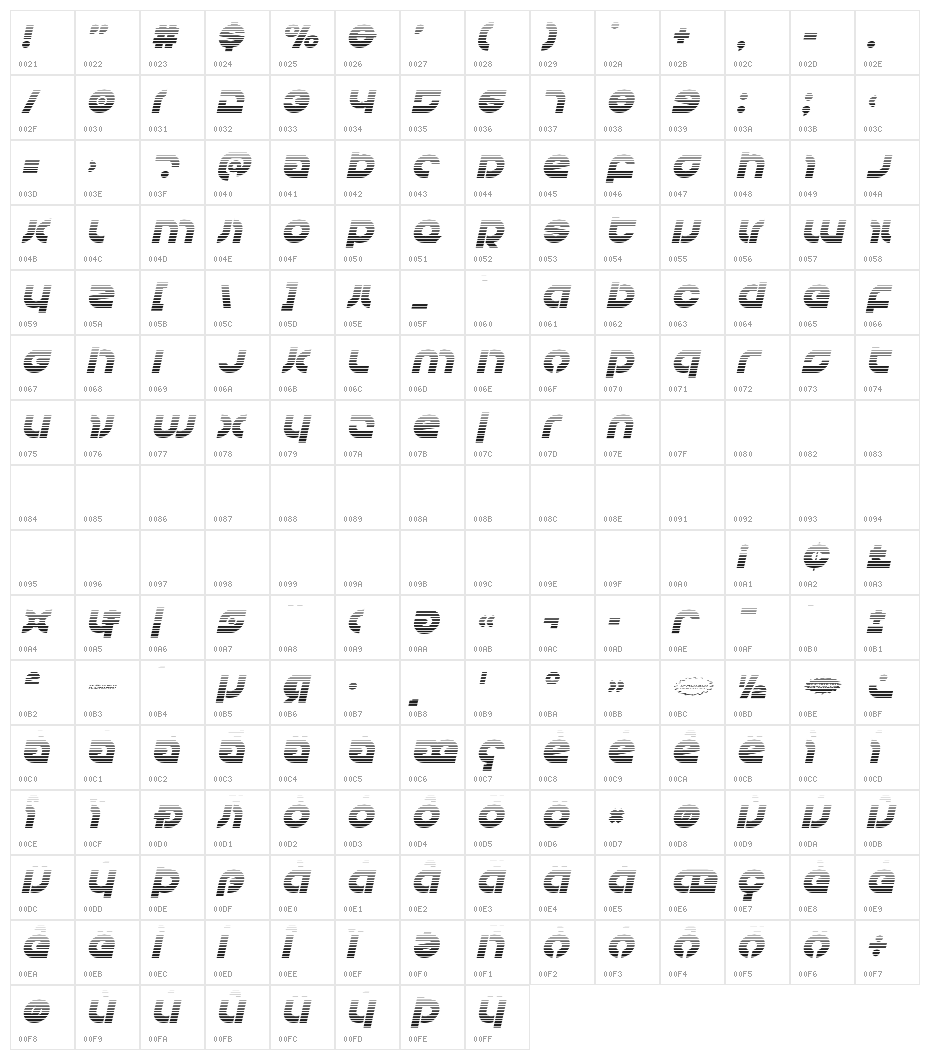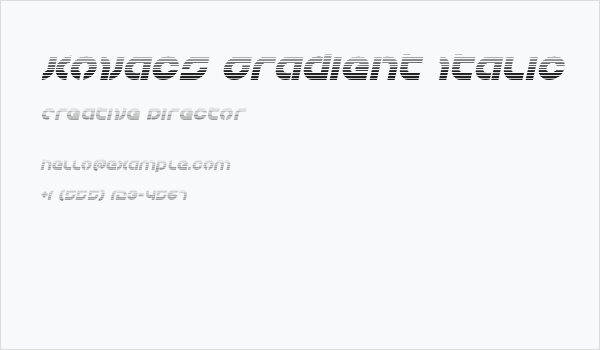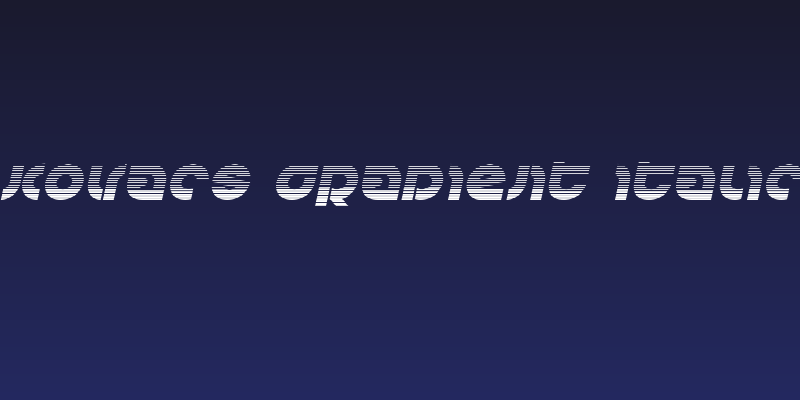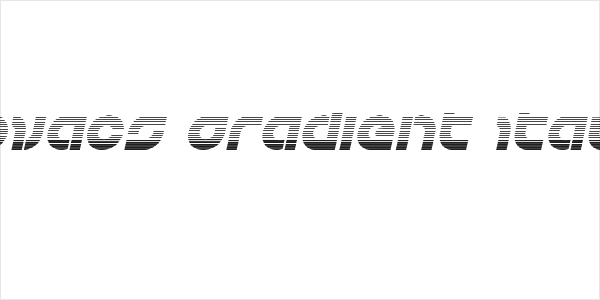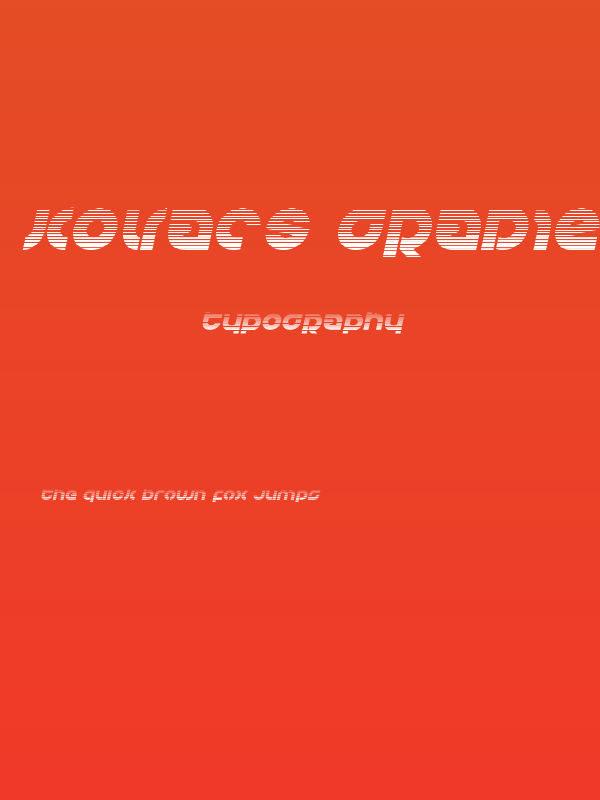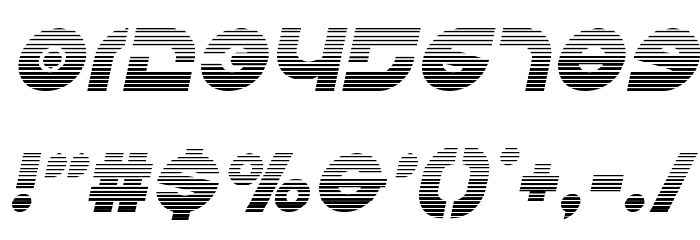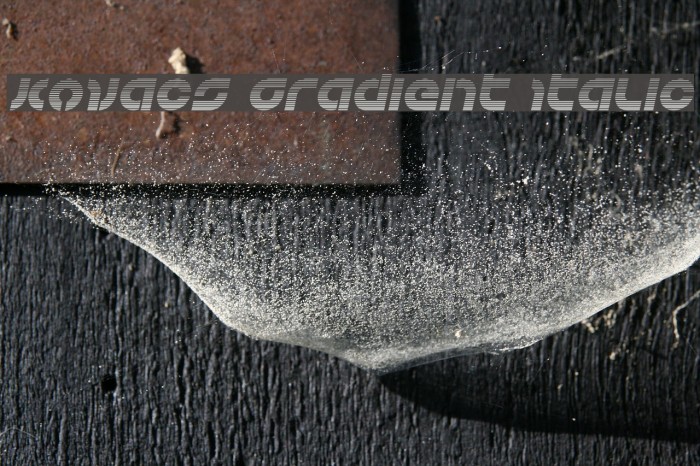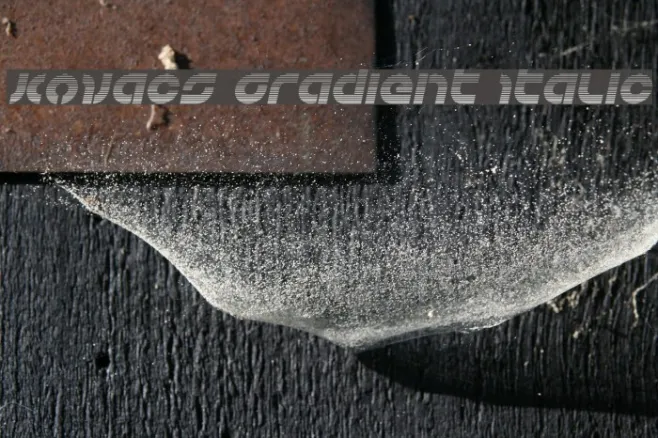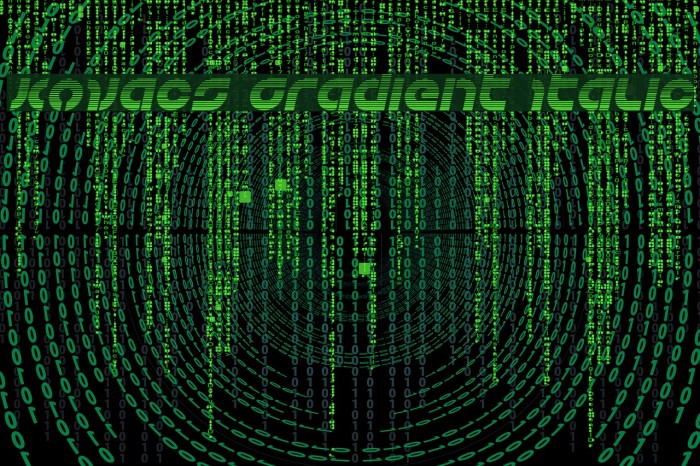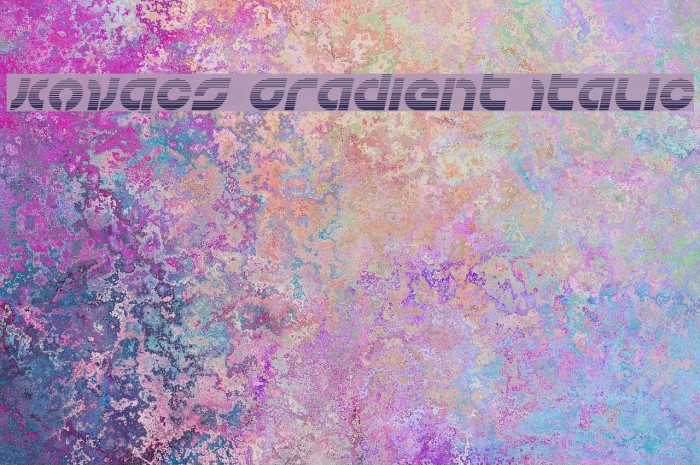
Kovacs Gradient Italic Font
| Caso de uso | Logos, Headlines, Posters |
| Proyectos propuestos | Ideal for futuristic branding, tech-related designs, and creative advertising campaigns. |